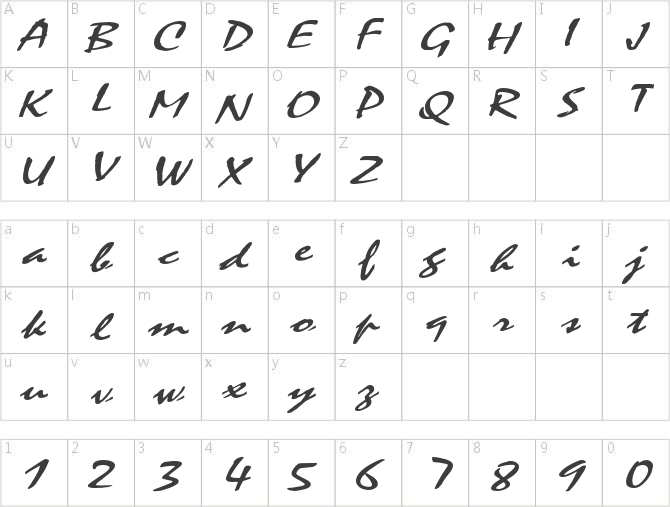
Mystic-Extended-Italic 詳情頁
字體名稱: Mystic-
Mystic-Extended-Italic
Mystic-Extended-Italic介紹
Mystic-Extended-Italic字體字庫是一款讓人賞心悅目、百看不厭的英文字體,適合各類廣告和產品包裝設計應用,字體大小0.1MB,格式為ttf字體,上傳用戶是gagilang,作者/版權方為未知